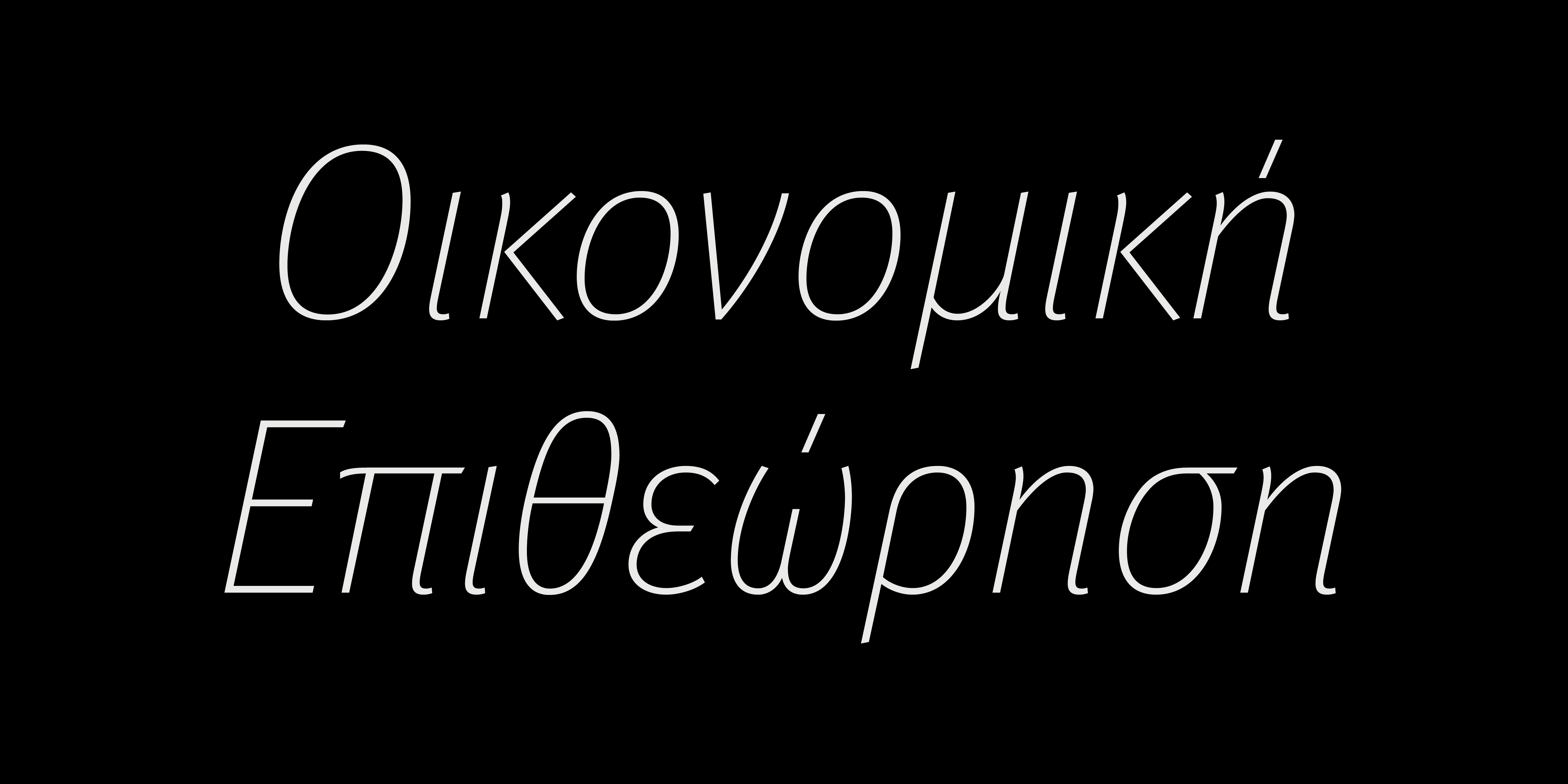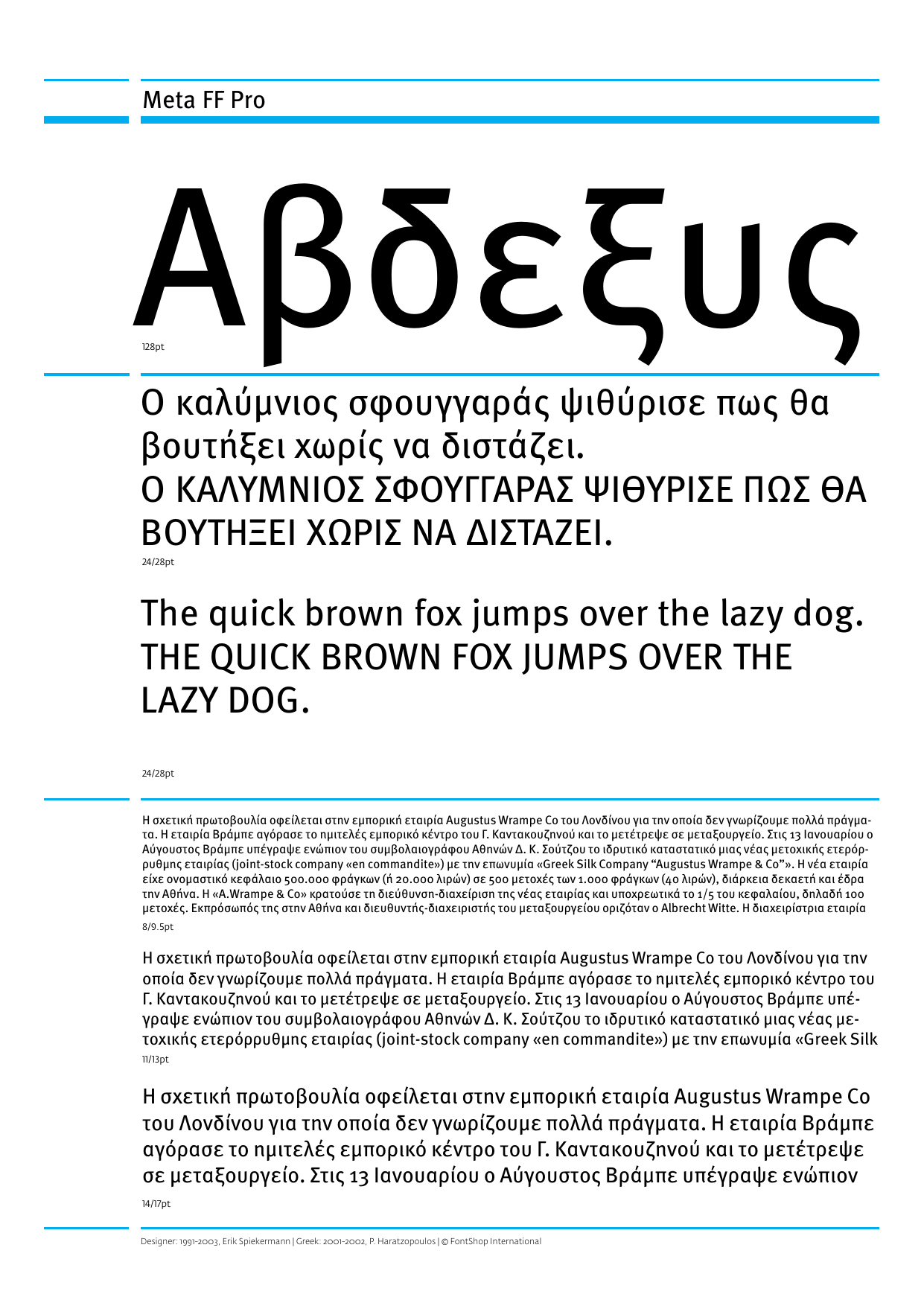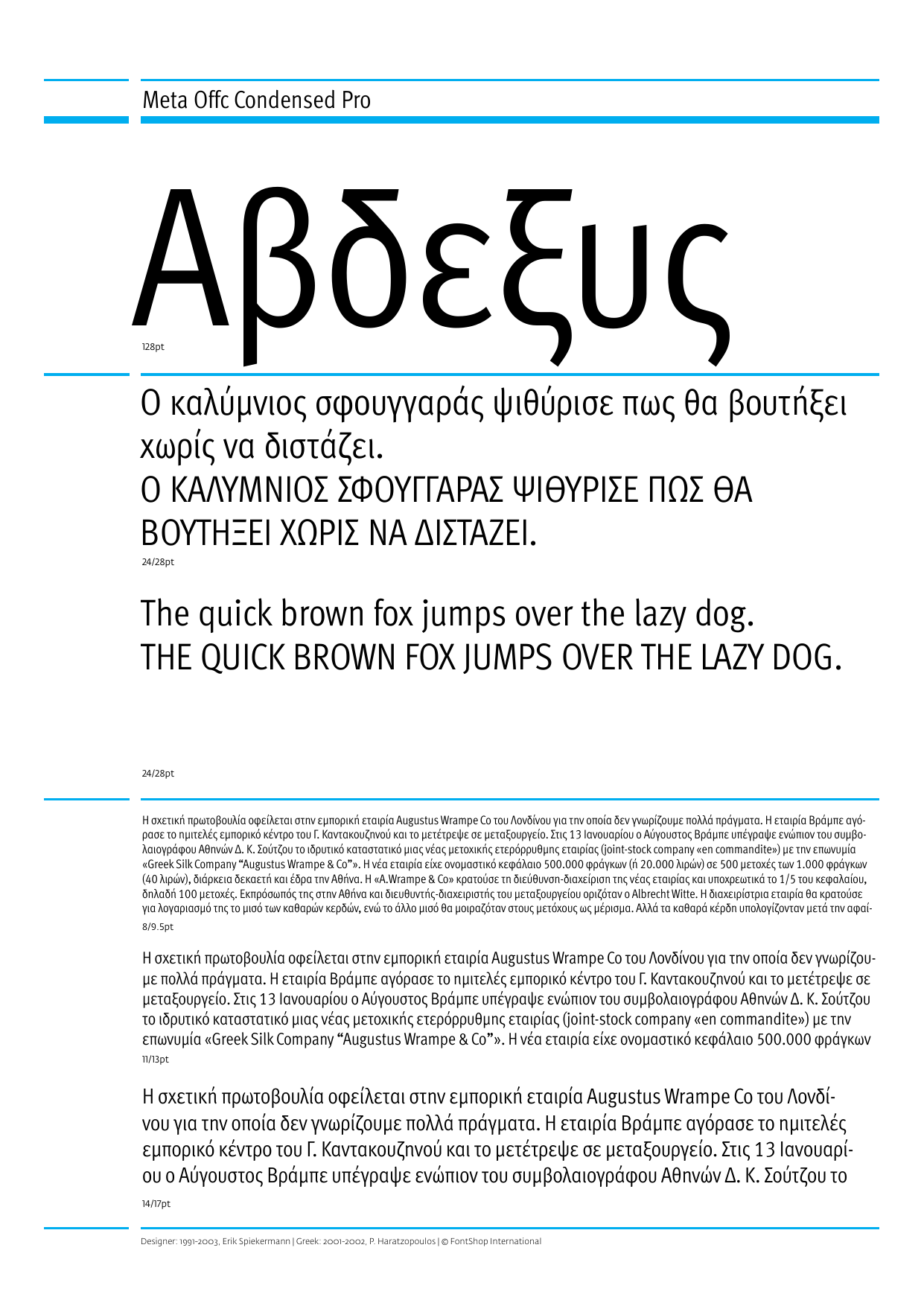
Meta Pro Collection
Meta Pro
Thin Thin Italic Hairline Italic Light Light Italic Normal Normal Italic Book Book Italic Medium Medium Italic Bold Bold Italic Black Black ItalicMeta Condensed Pro
Condensed Normal Italic Condensed Book Italic Condensed Medium Condensed Bold Italic Condensed Extrabold Condensed Black ItalicΤα FF Meta σχεδιάστηκαν από τον Erik Spiekermann, ιδρυτικό μέλος της FontShop International, κορυφαίο γραφίστα και σχεδιαστή της εποχής μας και επικεφαλής του MetaDesign. Ο αρχικός σχεδιασμός (1985), αποσκοπούσε στη χρήση της γραμματοσειράς σε τίτλους ή κείμενα μικρών στιγμών. Παρά τον αρχικό τους σκοπό, τα FF Meta πολύ γρήγορα έγιναν μια από τις δημοφιλέστερες γραμματοσειρές της εποχής των υπολογιστών και αναφέρονται ως τα Helvetica της δεκαετίας του ’90. Ο εξελληνισμός από τον Παναγιώτη Χαρατζόπουλο στηρίχθηκε στην ελληνική εκδοχή της FF Meta που έγινε από τον Spiekermann και το MetaDesign για τη σηματοδότηση της πόλης του Ναυπλίου.